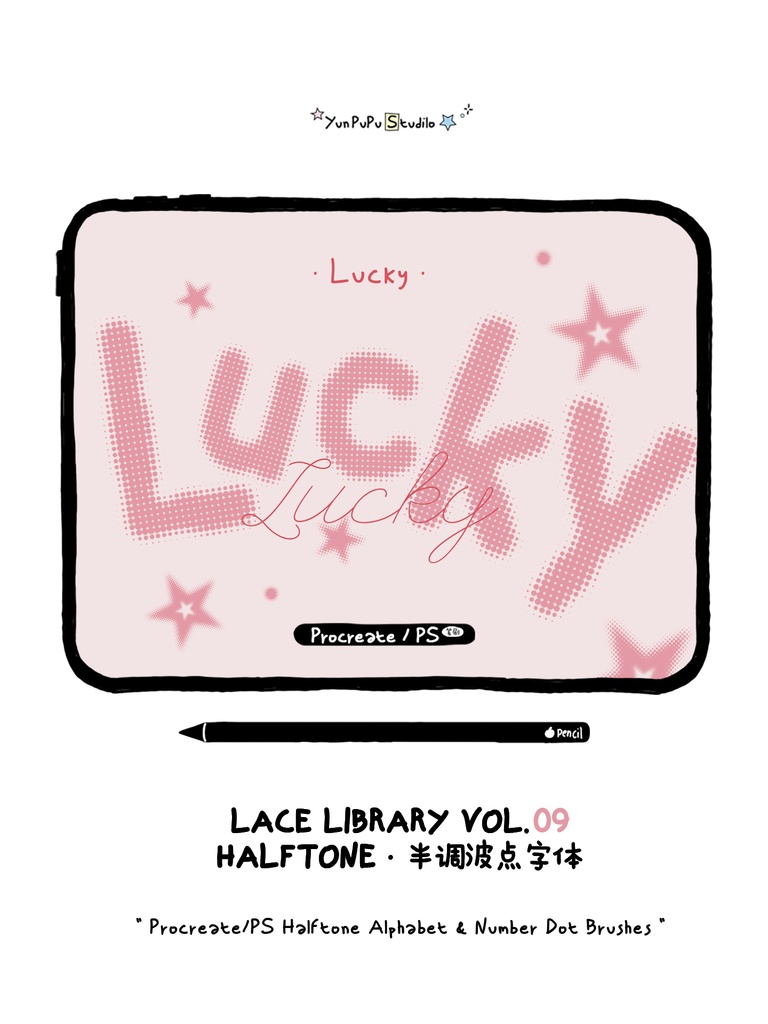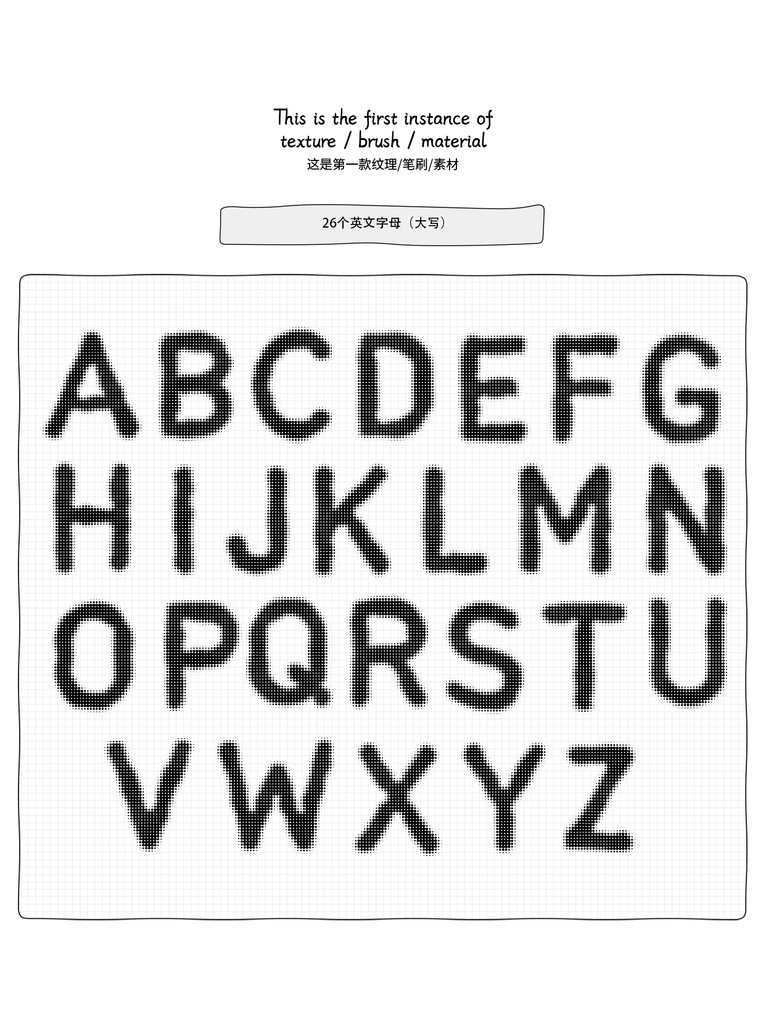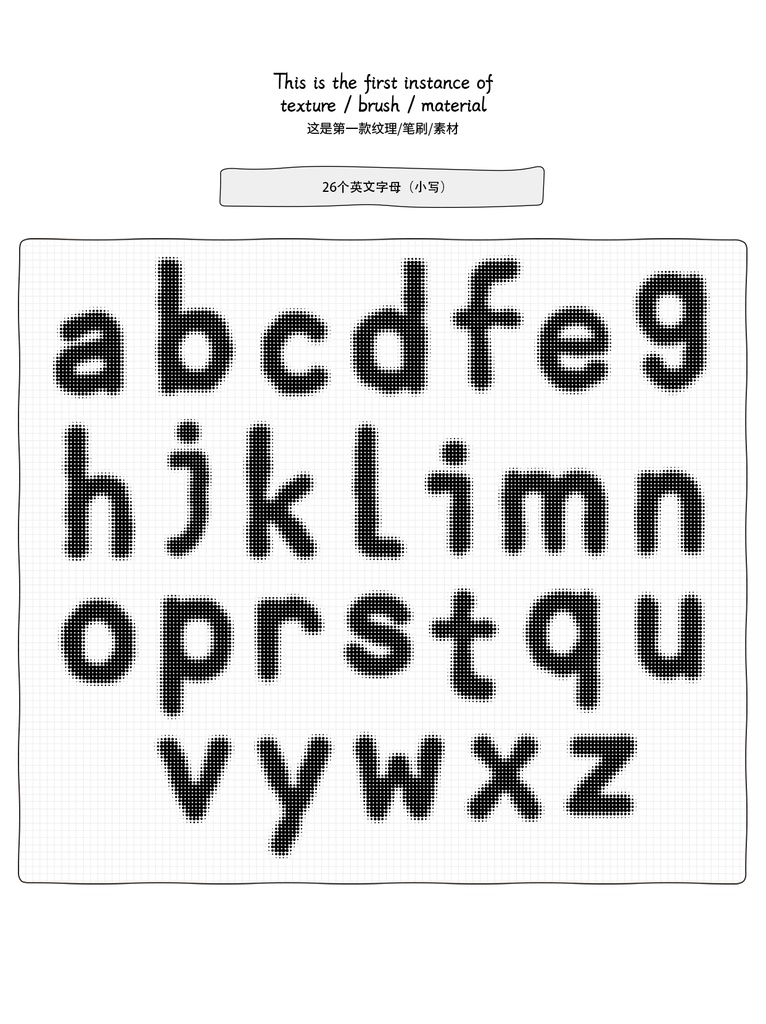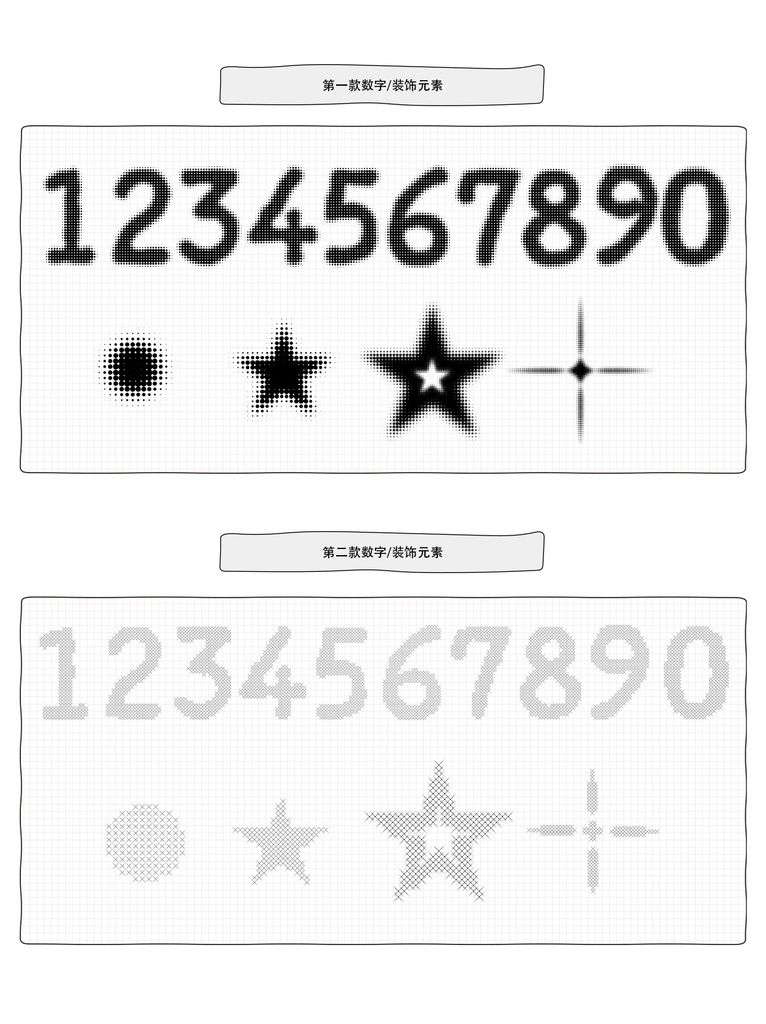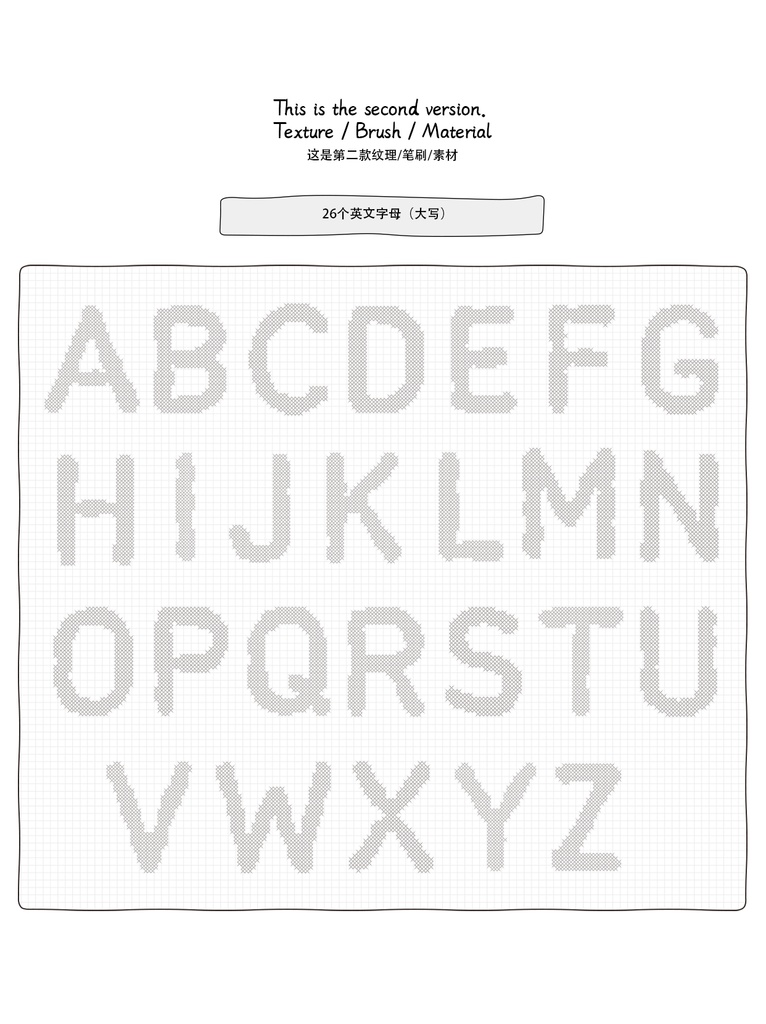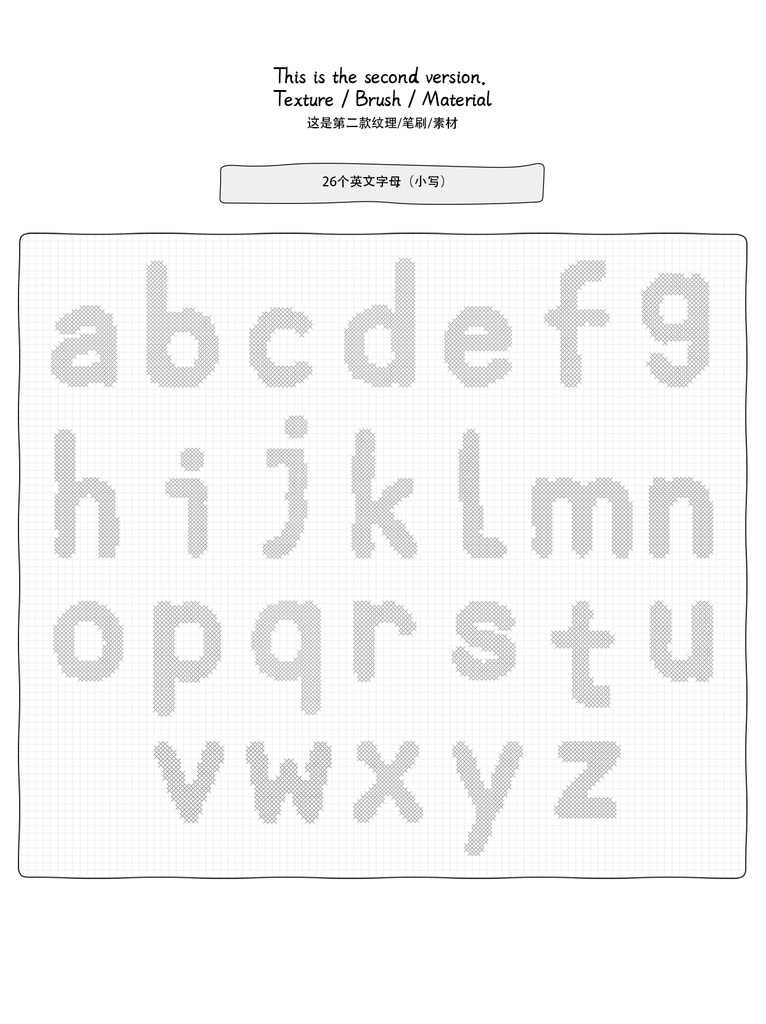
Procreate・PS 対応 ハーフトーン水玉フォント装飾ブラシ|PSD デザイン素材
かわいいハーフトーンのドット加工で、デザインに小さな文字アクセントをプラスしましょう ✦ Lace Library Vol.09 – Halftone(ハーフトーン文字) は、アルファベット・数字・遊び心のあるドットエレメントを収録したデコレーションブラシセットです。 イラスト、デジタル手帳、ステッカー、ラベル、ポスターなど、さまざまなクリエイティブ作品にかわいいディテールを加えるのにぴったりです。 商品内容: ✦ 大文字アルファベットブラシ 26種類(A-Z) ✦ 小文字アルファベットブラシ 26種類(a-z) ✦ 数字&デコレーションエレメントブラシ ✦ Procreate ブラシファイル(.brushset) ✦ Photoshop ブラシファイル(.ABR) ✦ 個人利用・商用利用ライセンス付き YunPuPu Studio オリジナルデザイン ☁️